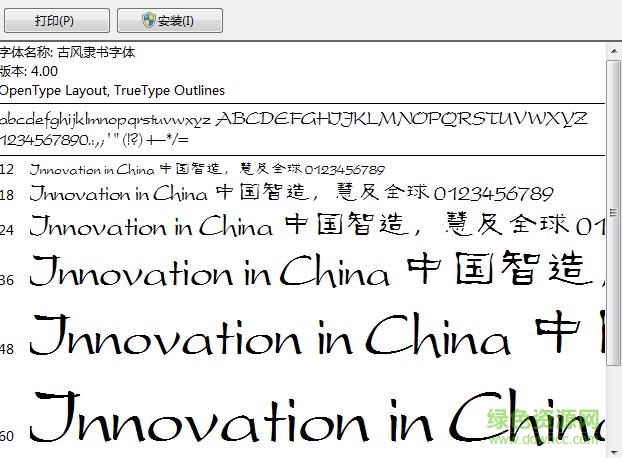
古風(fēng)隸書字體是一款采用隸書打造的電腦字體,保留首尾波折的外形,給人非常舒適好看的感覺,深受廣大書法家的喜愛,喜歡這款字體歡迎下載使用!
古風(fēng)隸書字體是一款根據(jù)古代隸書書法打造的中文字體,筆畫上保留深化了波折的元素,由于考慮到整體的可塑性,起收處弱化方筆加強(qiáng)圓筆畫,適合各大廣告標(biāo)題內(nèi)容的應(yīng)用!